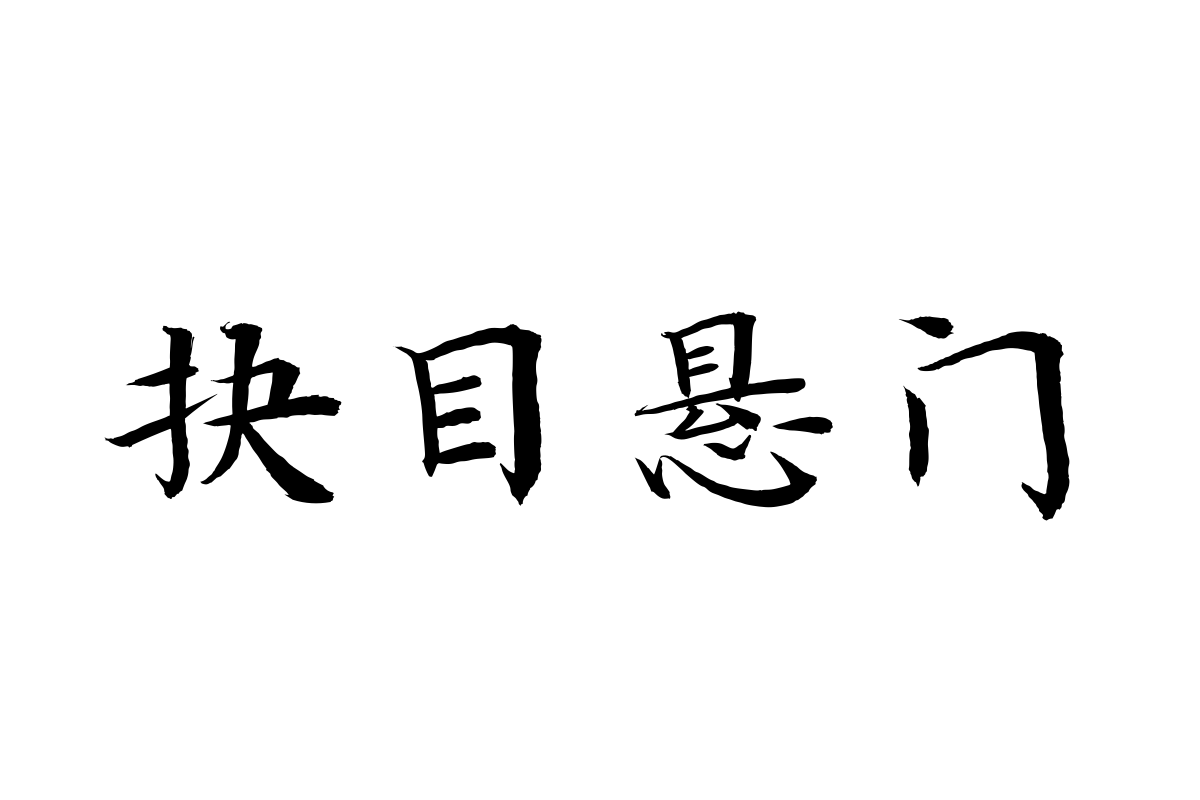
汉仪闫锐敏楷书是一款由汉仪公司开发的中文字体,主要用于书法和书写设计。这款字体的特点是笔画流畅、字形规整,适合用于书法作品和手写笔记。
1. 笔画流畅:汉仪闫锐敏楷书的笔画线条流畅自然,没有过多的折弯和转折,给人一种轻松愉悦的感觉。
2. 字形规整:这款字体的字形规整,上下左右都有一定的比例关系,使得整体看起来更加和谐统一。
3. 适合书法:由于其笔画流畅和字形规整的特点,汉仪闫锐敏楷书非常适合用于书法创作,可以很好地展现书法家的技艺和风格。
4. 适合手写笔记:这款字体也非常适合用于手写笔记,因为其笔画流畅和字形规整的特点,使得书写起来更加顺畅,不易出错。
总的来说,汉仪闫锐敏楷书是一款非常实用的中文字体,无论是用于书法还是手写笔记,都能展现出良好的效果。